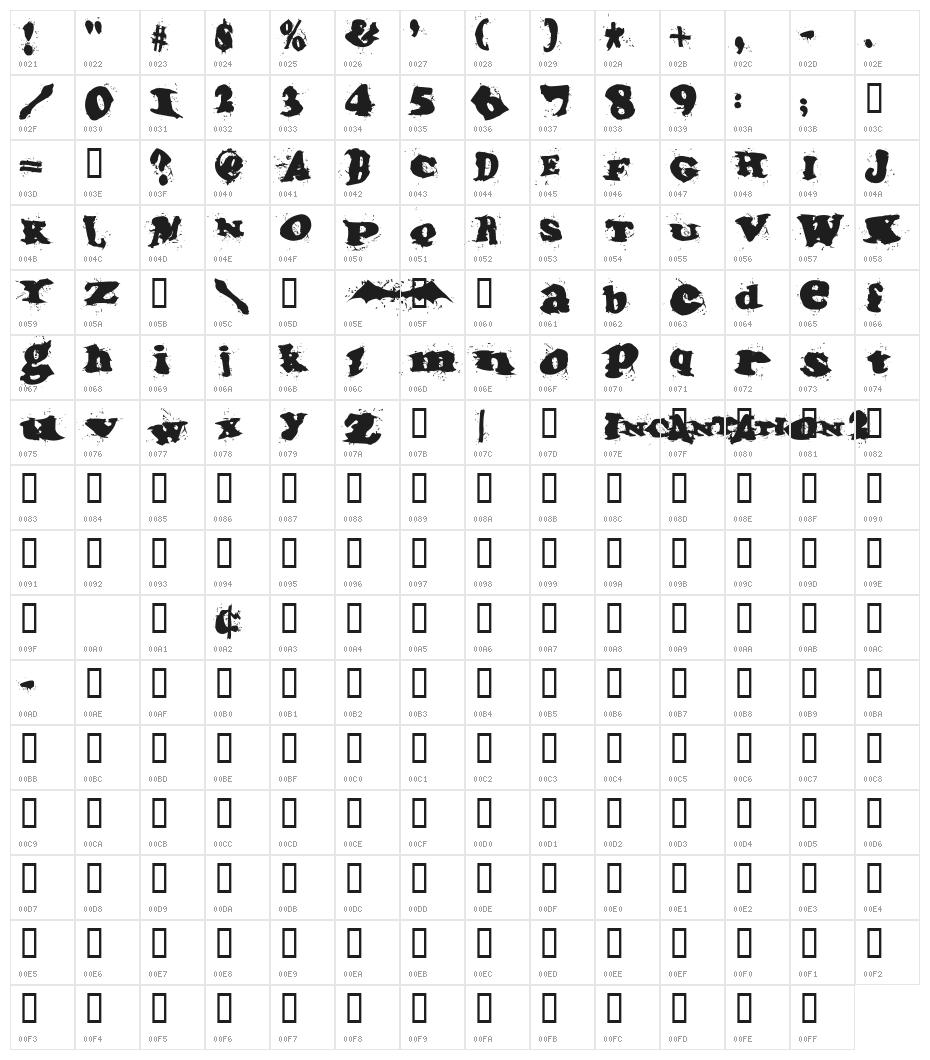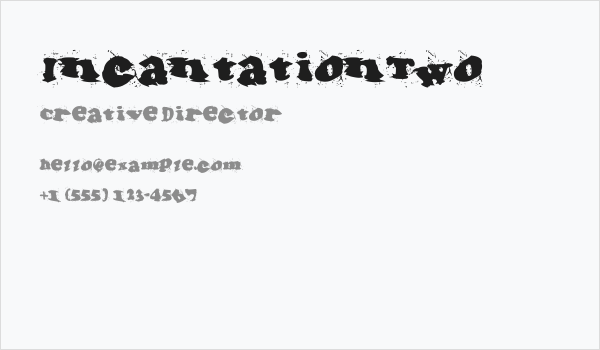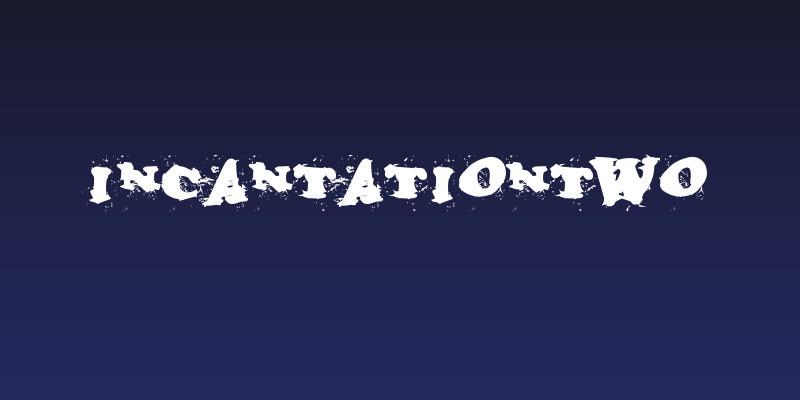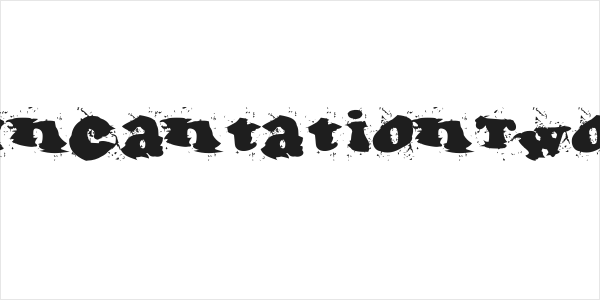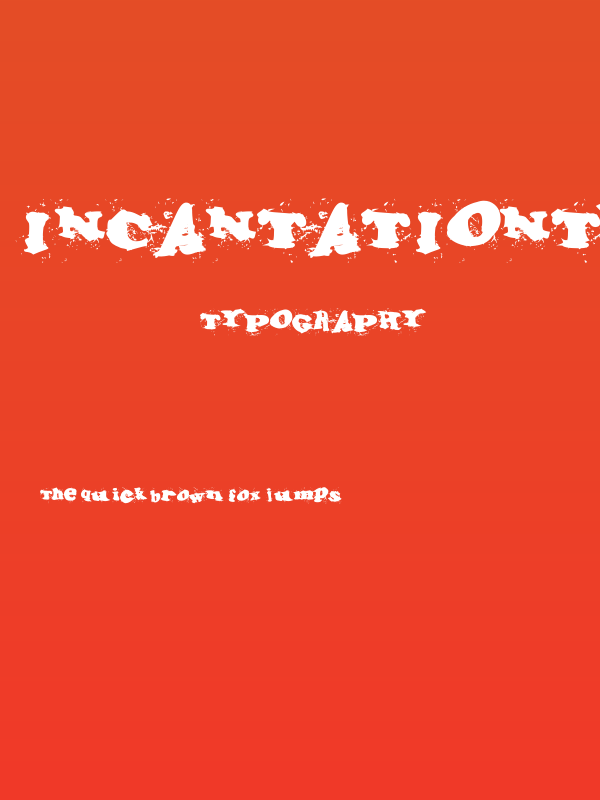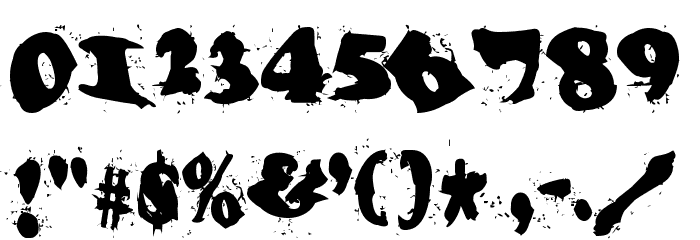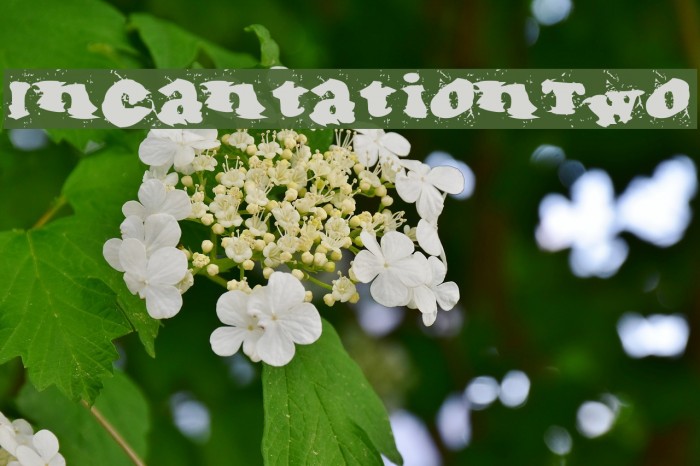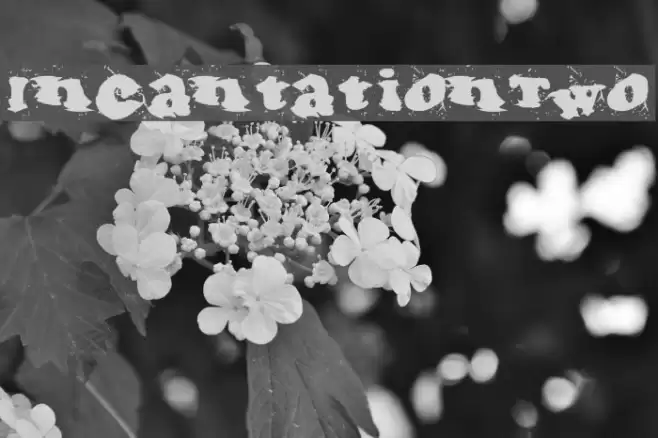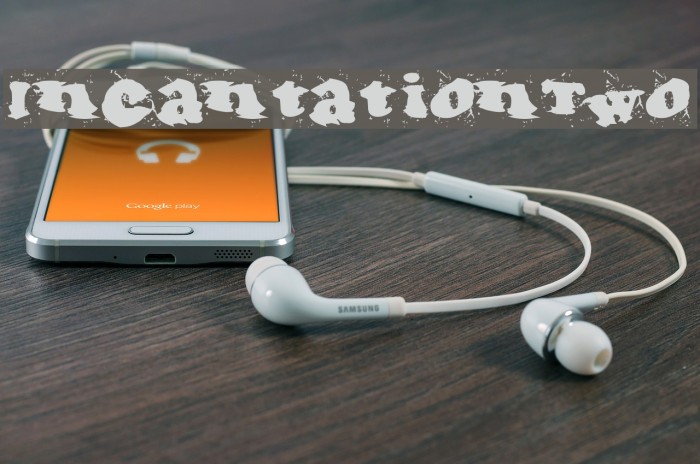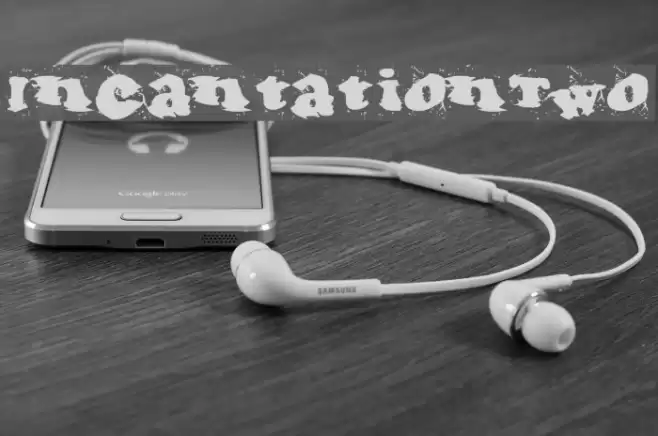
IncantationTwo Font
✎ Distorted Eroded
| Vorgeschlagene Projekte | Ideal for album covers, posters, horror-themed designs, and edgy branding projects. |